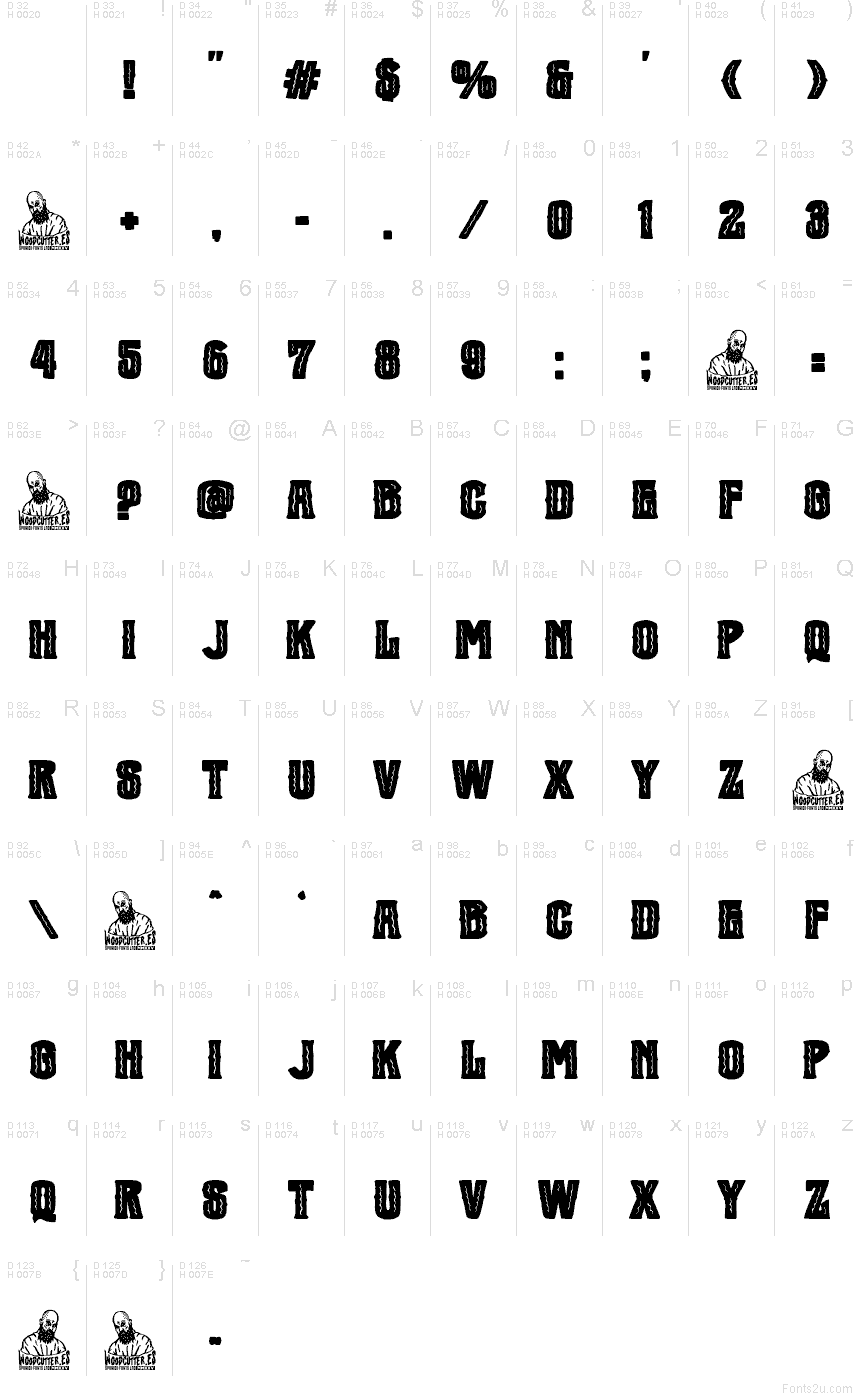
Bourbon Club Solid
Bourbon Club Solid, di Woodcutter Manero, è un font display gratuito in stile western, caratterizzato dalla grinta ruvida delle scritte dei vecchi saloon. Le lettere sono pesanti, piene e leggermente irregolari, con solchi verticali che le fanno sembrare intagliate nel legno, vissute e autentiche, ben lontane da una rifinitura troppo leziosa.
Si adatta perfettamente a etichette di whisky, branding di locali, poster di rodeo, flyer per eventi country e packaging audaci che richiedono un font gratuito con un pizzico di carattere "frontiera", senza sfociare nel decorativo fine a se stesso. Usalo per titoli brevi, copertine, scritte d'apertura o monogrammi: quelle silhouette spesse e le texture incise rendono al meglio quando le parole sono poche.